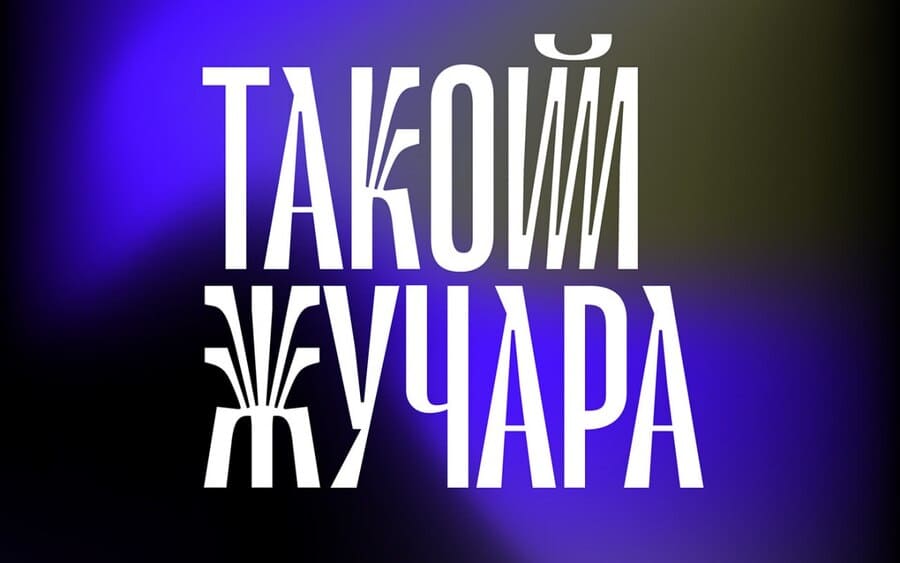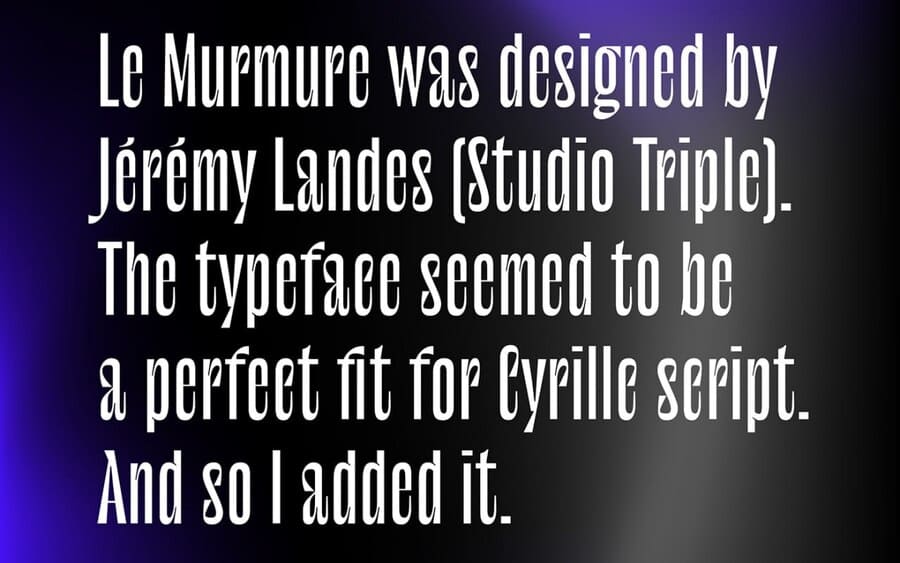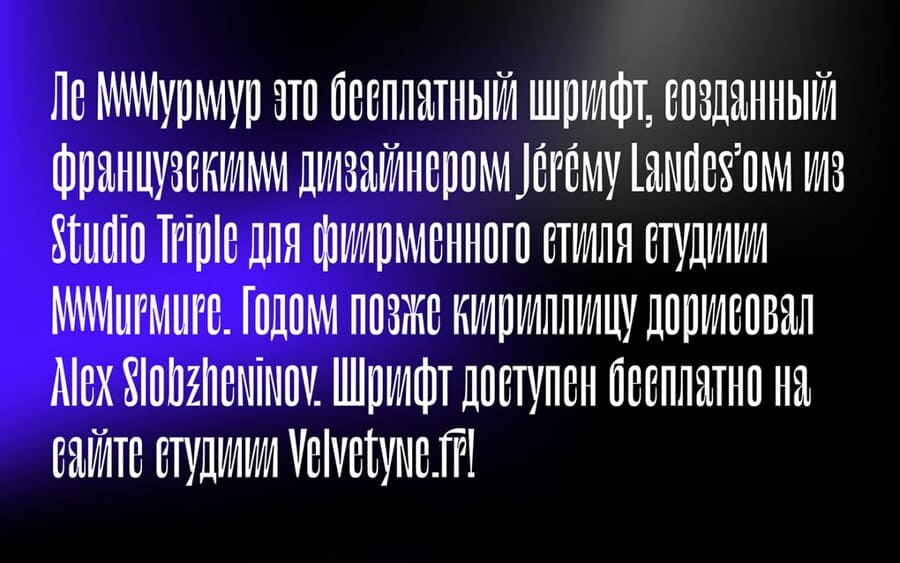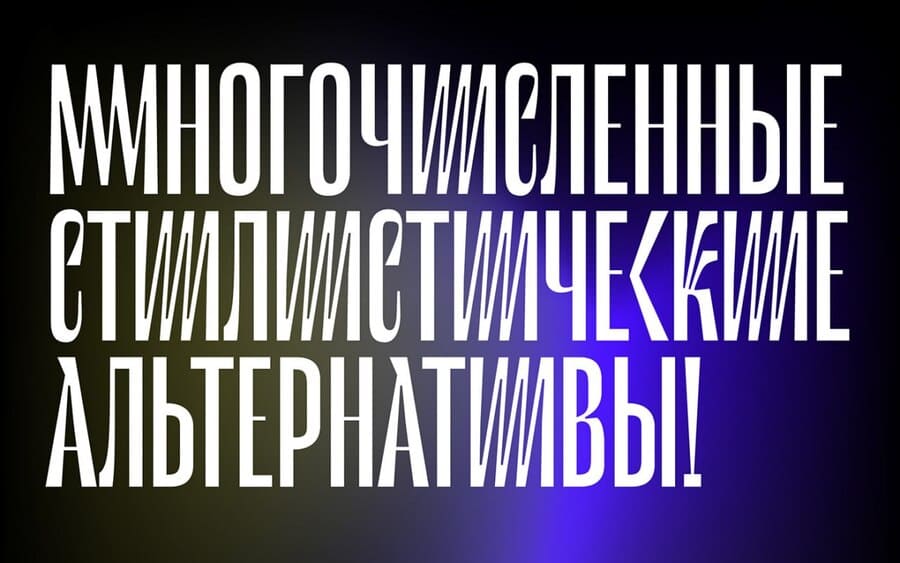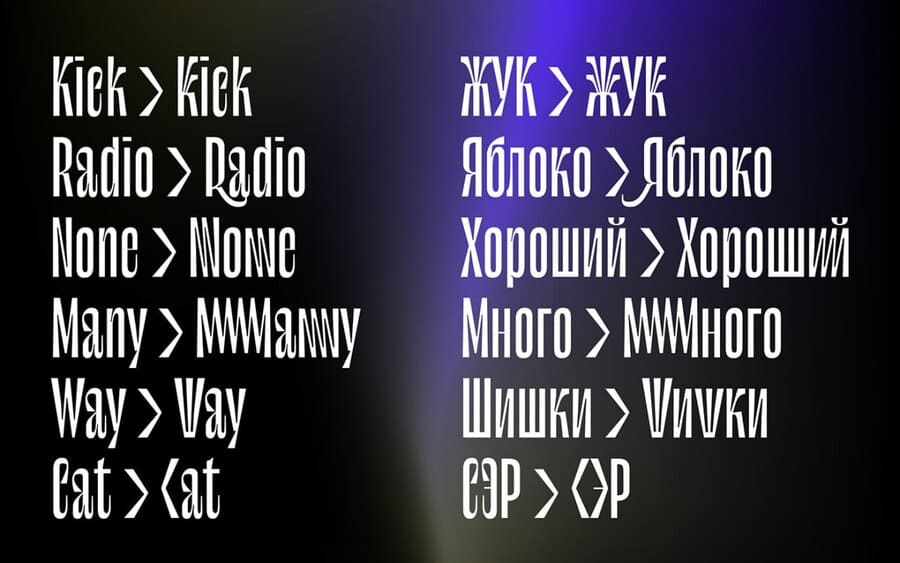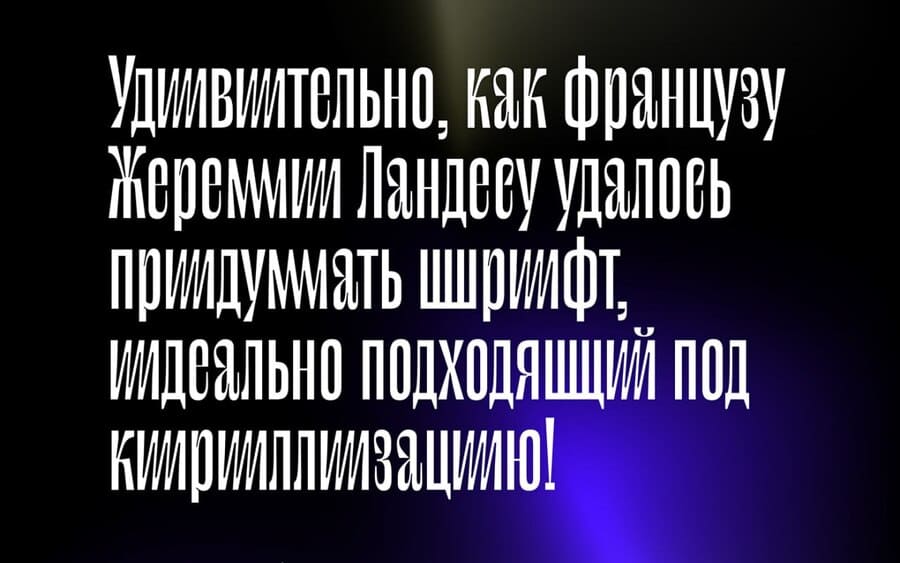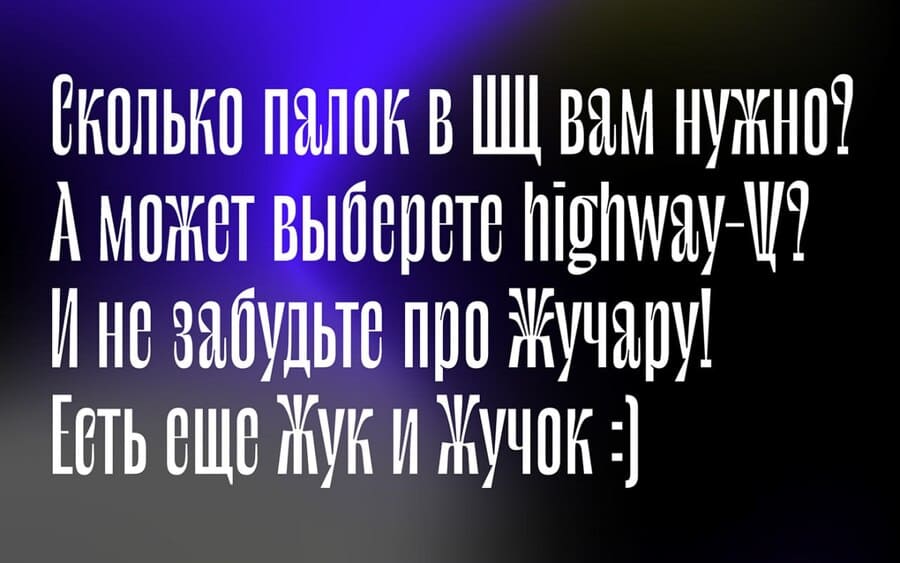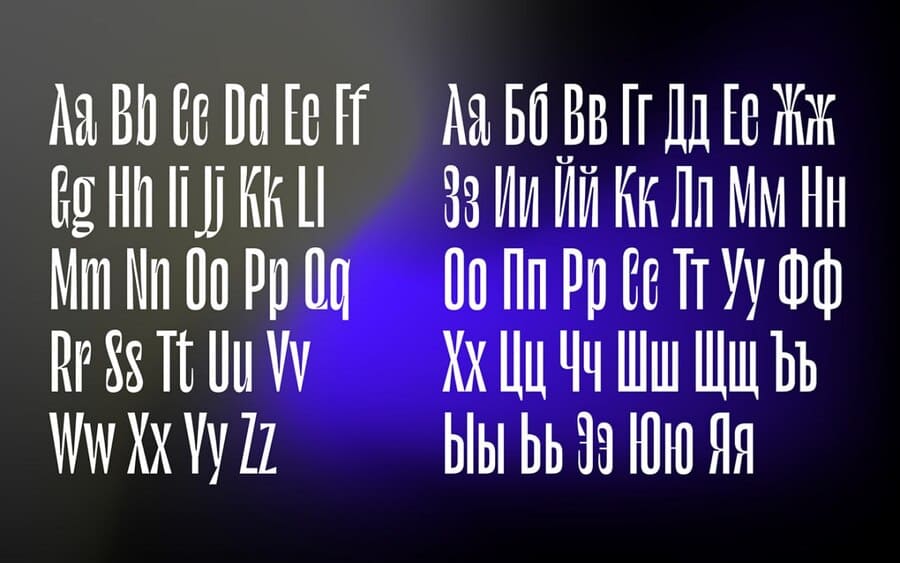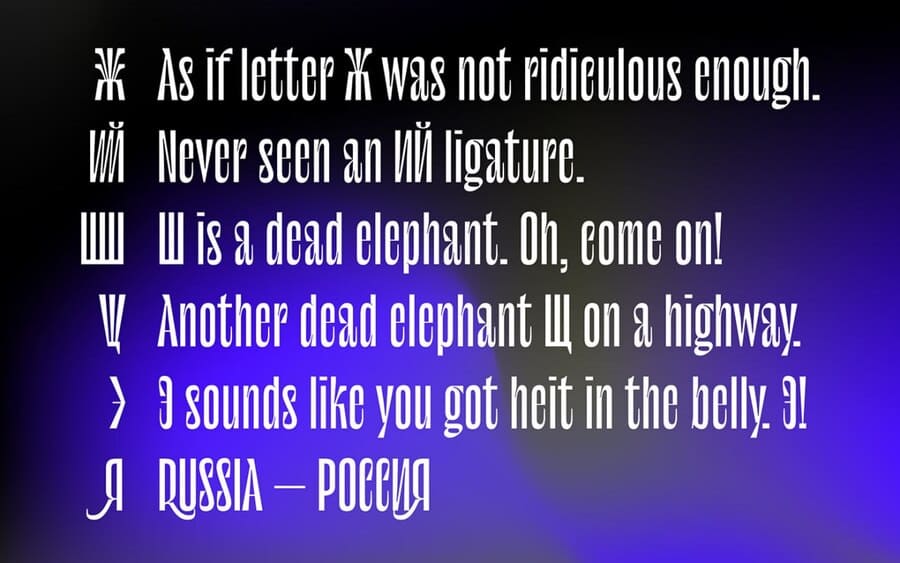
Le Murmure Cyrillic Font
Le Murmure Cyrillic
Le Murmure Cyrillic Font
About the product: Le Murmure Cyrillic Font
✦ Le Murmure – это шрифт, разработанный Jérémy Landes для агентства Murmure. Кириллицу позже добавил Alex Slobzheninov.